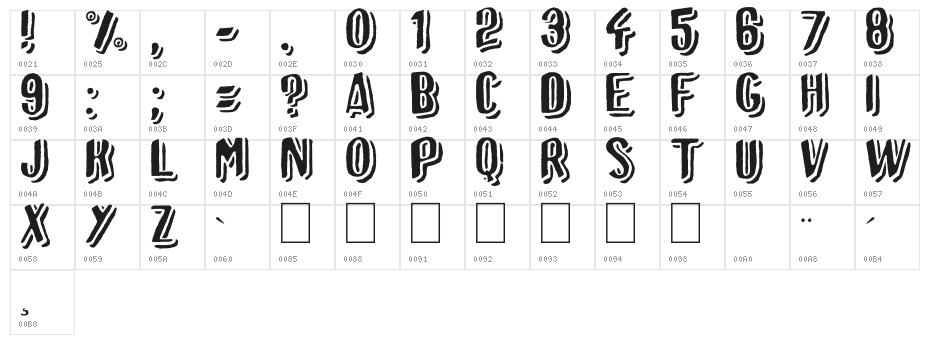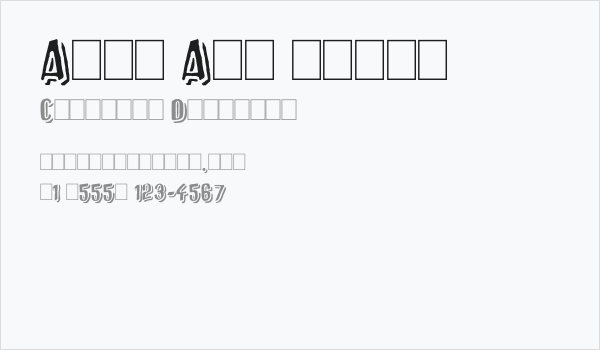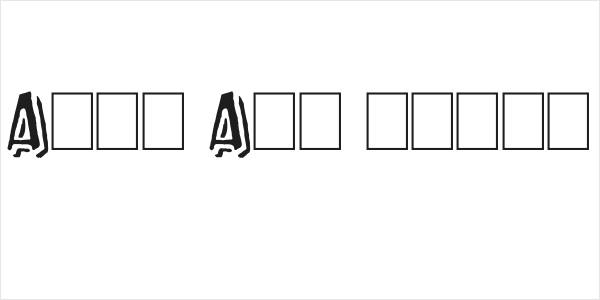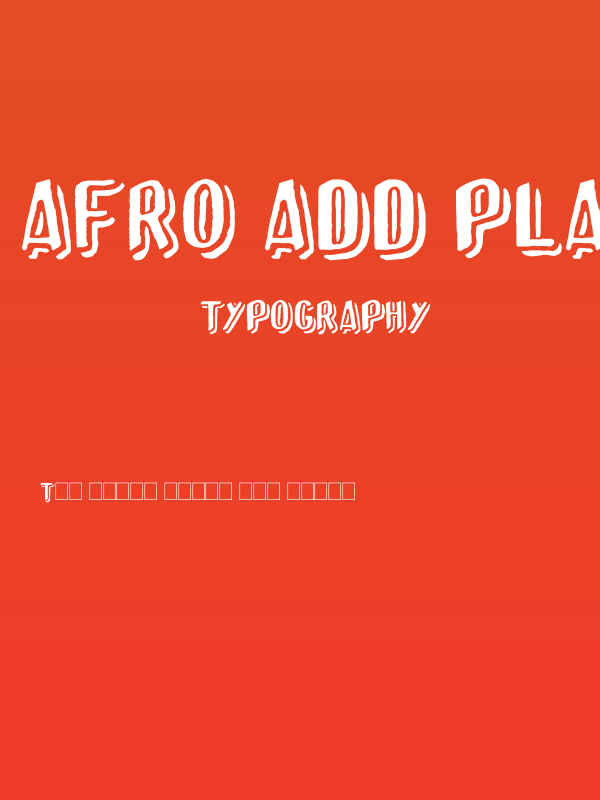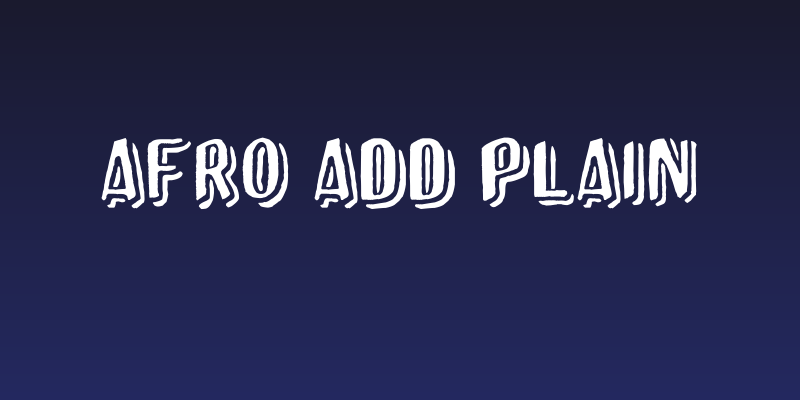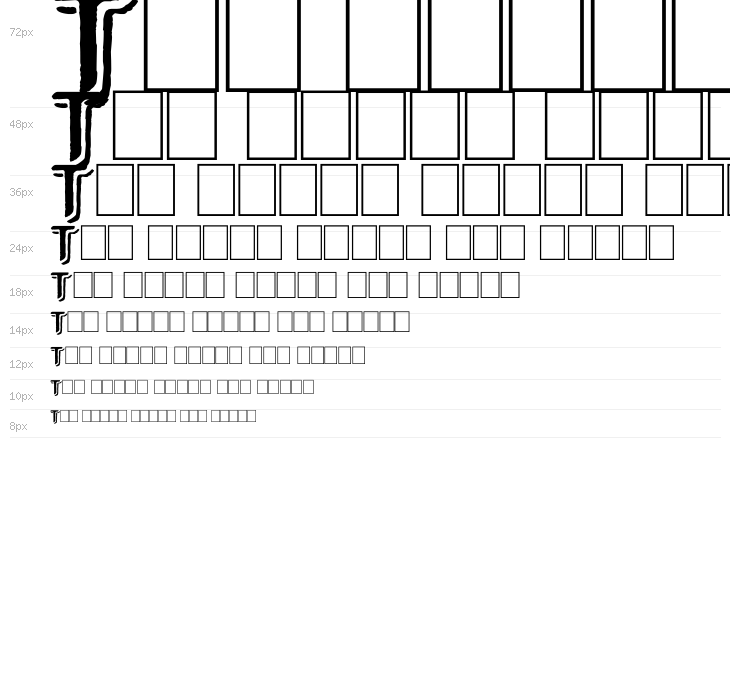
Afro Add plain Font
✎ Graffiti
| 推荐项目 | Ideal for posters, album covers, street art designs, and branding projects that require a bold, expressive typeface. |